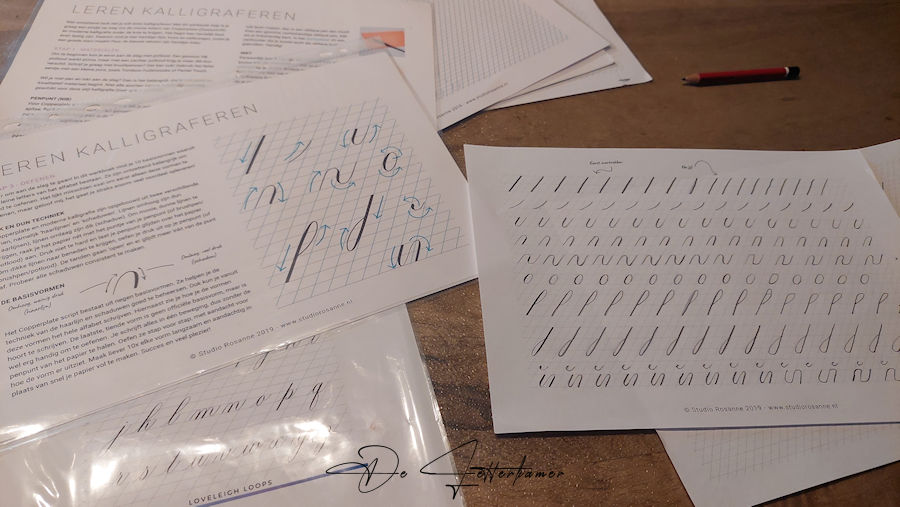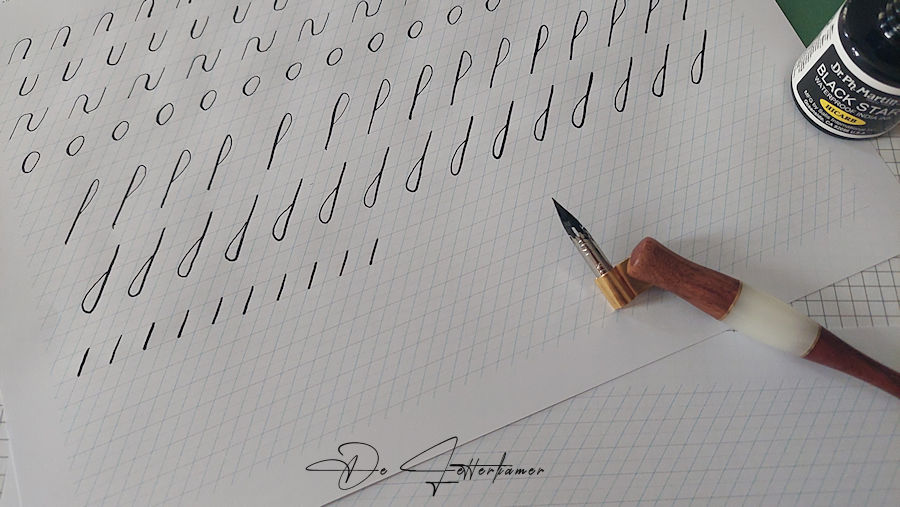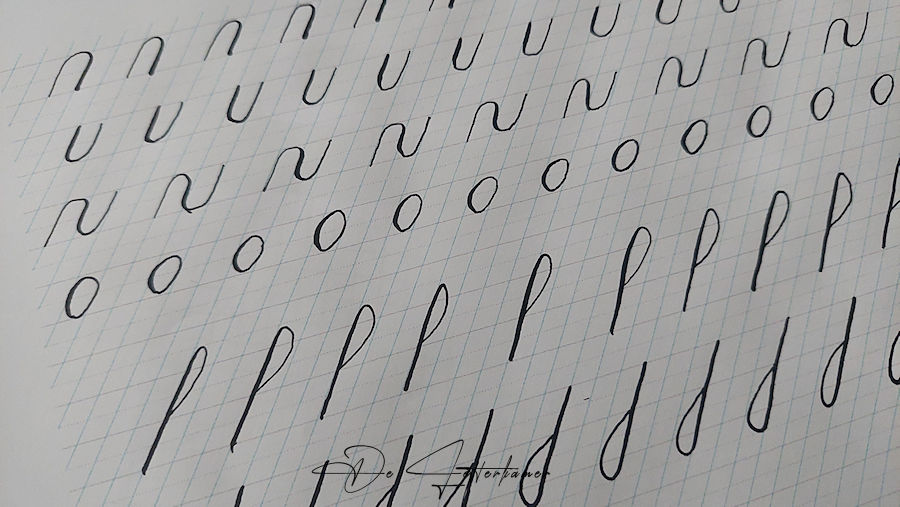
De zon gaat onder, en mijn pen komt tevoorschijn. We gaan weer verder. Alle materiaal ligt voor me, en we gaan voor de 1ste keer werken met de oblique penhouder.
De oblique penhouder.
Ik was dus razend benieuwd. Nog steeds met mijn gebruikelijke inkt “Dr. Ph. Martin’s Hi-Carb Inkt”, maar ik vermoed dat deze iets te dik is, ze vloeit niet goed genoeg volgens mij. Ondertussen heb ik een mail ontvangen dat de inkt “Kuretake Sumi inkt 60ml” binnen is, en besteld kan worden. Ik heb deze ook meteen besteld. Deze laatste werd het meest aanbevolen, qua dikte van de inkt en voor beginners.
De eerste basisvormen zijn getekend of geschreven. Het gaat beter dan verwacht. De penhouder ligt goed in de hand, en zeer licht. De nib “Nikko G” zit goed vast. De inkt vind ik persoonlijk minder, deze lijkt teveel vastplakken aan de nib. Of het kan zijn dat ik de inkt moet verdunnen. Maar geen gedemineraliseerd water in huis om te verdunnen, dus ja dan maar even zo, kraanwater zou niet goed zijn, met de kalk er in enzo… en hier in mijn streek zit enorm veel kalk in het water, dus dit ga ik niet doen.
Zo af en toe, kuis ik de nib af aan een papieren doekje. Dat gaat ook om de tevele inkt er af te halen. De vorige keer had ik ook problemen. Nochtans de nib is goed ontvet.
Dit zijn mijn geschreven basisvormen. Die lussen daar ben ik nog steeds niet tevreden over.
Het zal toch enige tijd duren vooraleer deze zijn zoals ik het wil hebben. De oblique penhouder heeft het schitterend doorstaan, ik ben dus een zeer tevreden iemand.
Links op de foto zijn de basisvormen, die ik nu aan het oefenen ben.
Zo, het klein uurtje is al verstreken, het is heel snel voorbij en gelukkig ook snel opgeruimd. Kalligrafie is zeer toegankelijk, het vraag niet veel tijd en ook niet veel van het budget. Je kan ook tussendoor oefenen met een brushpen. Zeer handig!